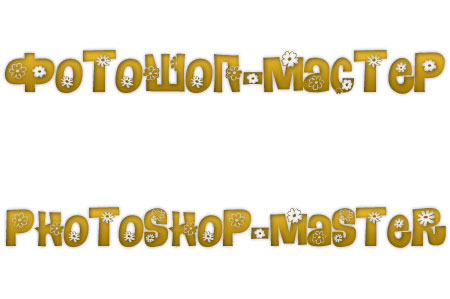
Ах закачаешся какой шрифт
КРАСИВЕНЬКО !!!!!!
Спасибо! Отличный, очень красивый шрифт
как долго я искала нечто подобное, и как неожиданно нашла на своем любимом сайте! касс!!! спасибки!!!
Спасибо! Как раз для детской фотки!
Супер)))))
суууупер!! я такой классный!! спасибочки за этот шрифтик!!!!!
мне понравился! Шэп!